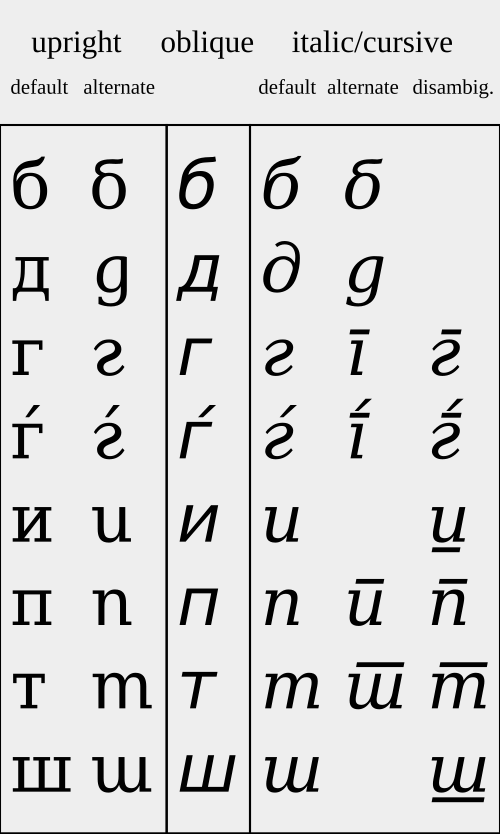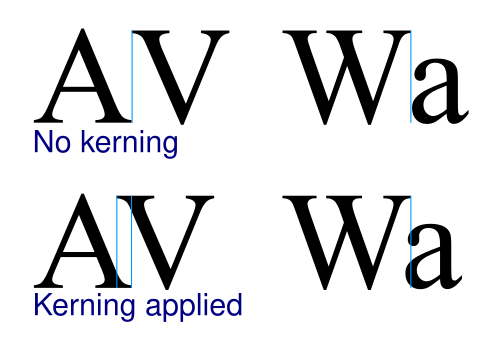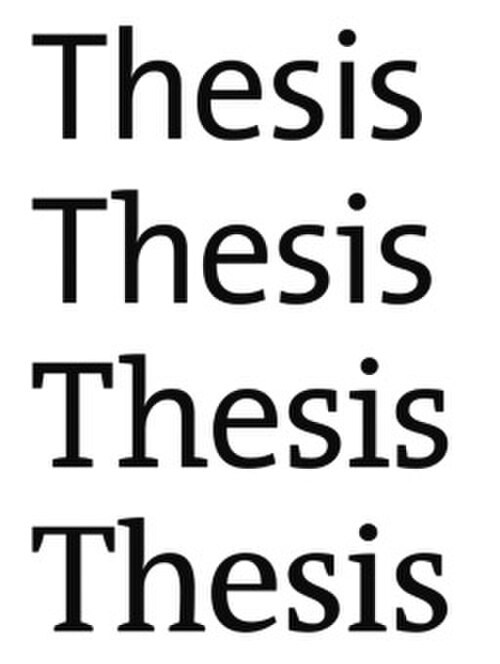
نوع الخط
في الطباعة المعدنية ، يُعرَّف الخط بأنه حجم ووزن ونمط محددين لنوع الخط ، والذي يُعرَّف بأنه مجموعة الخطوط التي تشترك في تصميم عام. على سبيل المثال، يتضمن خط Bauer Bodoni (الموضح في الشكل) الخطوط " Roman 12pt" (أو "عادي") و" bold 12pt " و" italic 12pt " ؛ ويتوفر كل نمط من هذه الأنماط أيضًا في مجموعة من الأحجام الشائعة الأخرى . في الطباعة التقليدية، كانت الخطوط تُصنع فعليًا باستخدام حروف معدنية أو خشبية، مع وجود خط لكل حجم.
في مجال الحوسبة المعاصرة، يُستخدم مصطلحا "الخط" و "نمط الخط" غالبًا بشكل متبادل للإشارة إلى خطوط الحاسوب ، [ 1 ] ومعظمها قابل للتكبير والتصغير. وبينما تستخدم أحجام الخط المختلفة عادةً نفس أشكال الأحرف ، فليس من النادر أن يتضمن الخط عناصر تصميم مختلفة لتحسين سهولة القراءة أو التأثير، خاصةً عند الأحجام الكبيرة أو الصغيرة. تُوزَّع خطوط الحاسوب كملفات، وقد يحتوي كل ملف على وزن واحد أو أكثر ونمط واحد أو أكثر من أنماط الخط.
التهجئة وعلم أصول الكلمات
كلمة font ( في الولايات المتحدة) أو fount (في المملكة المتحدة التقليدية؛ وفي كلتا الحالتين تُنطق / fɒnt / ) مشتقة من الكلمة الفرنسية الوسطى fonte ، والتي تعني " الحديد الزهر". [ 2 ] يشير المصطلح إلى عملية صب الحروف المعدنية في مصنع صب الحروف .
أصبح خط التهجئة ، الذي كان يُستخدم في الأصل في الولايات المتحدة فقط، هو الخط المقبول حاليًا. أما خط Fount ، الذي كان يُستخدم تاريخيًا في المملكة المتحدة ودول الكومنولث ، [ 3 ] فيُعتبر قديمًا.
نوع المعدن
في مطبعة يدوية ( طباعة بارزة )، يشير مصطلح "الخط" إلى مجموعة كاملة من حروف الطباعة المعدنية المستخدمة في طباعة صفحة كاملة. وتُسمى الحروف الكبيرة والصغيرة نسبةً إلى موضع حرف الطباعة المعدني في الطباعة اليدوية: الحرف الكبير الأبعد أو الحرف الصغير الأقرب. ويُستخدم المصطلحان "majuscule" و "minuscule" للدلالة على هذا التمييز .
على عكس الخطوط الرقمية، لا يتضمن الخط المعدني تعريفًا واحدًا لكل حرف، بل يحتوي على أجزاء مادية أكثر للأحرف الشائعة الاستخدام (مثل حروف العلة والنقاط). عند شراء خط جديد، يُباع غالبًا على النحو التالي (على سبيل المثال، في الأبجدية اللاتينية): "12pt 14A 34a"، أي أنه خط بحجم 12 نقطة يحتوي على 14 حرف "A" كبير، و34 حرف "a" صغير.
أما بقية الأحرف، فكانت تُوفَّر بكميات مناسبة لتوزيع الحروف في تلك اللغة. بعض الأحرف المعدنية المطلوبة في الطباعة، مثل الشرطات والمسافات وفواصل ارتفاع الأسطر، لم تكن جزءًا من خط محدد، بل كانت قطعًا عامة يمكن استخدامها مع أي خط. [ 4 ] لا يزال يُطلق على تباعد الأسطر غالبًا اسم " التباعد "، لأن الشرائط المستخدمة لتباعد الأسطر كانت مصنوعة من الرصاص (بدلًا من السبيكة الأكثر صلابة المستخدمة في القطع الأخرى). صُنع شريط التباعد هذا من الرصاص لأنه معدن ألين من قطع الطباعة المعدنية المطروقة التقليدية (التي كانت تتكون جزئيًا من الرصاص والأنتيمون والقصدير )، وبالتالي ينضغط بسهولة أكبر عند تثبيته في "إطار" الطباعة (أي الحامل الذي يجمع جميع الأحرف معًا).
في ثمانينيات وتسعينيات القرن التاسع عشر، تم اختراع الطباعة "بالرصاص الساخن" ، حيث يتم صب الحروف أثناء وضعها، إما قطعة قطعة (كما هو الحال في تقنية Monotype ) أو في أسطر كاملة من الحروف في وقت واحد (كما هو الحال في تقنية Linotype ).
صفات
إضافةً إلى ارتفاع الحرف، عند استخدام المعنى الميكانيكي للمصطلح، توجد عدة خصائص أخرى قد تميز الخطوط، مع العلم أنها تعتمد أيضاً على نظام الكتابة الذي يدعمه الخط. في أنظمة الكتابة الأبجدية الأوروبية ، أي اللاتينية والسيريلية واليونانية ، تتمثل الخصائص الرئيسية في عرض الخط (الوزن) ، والنمط أو الزاوية ، وعرض الحرف .
يُطلق على الخط العادي أو القياسي أحيانًا اسم "روماني " لتمييزه عن الخط العريض أو الرفيع ، وعن الخط المائل أو المائل المائل . غالبًا ما تُحذف الكلمة المفتاحية للحالة العادية الافتراضية في المتغيرات، ولا تُكرر أبدًا، وإلا لكانت تُكتب على النحو التالي: Bulmer regular italic ، Bulmer bold regular ، وحتى Bulmer regular . كما يُمكن أن يُشير مصطلح "روماني" إلى دعم الخط للغات، كاختصار لعبارة "أوروبية غربية".
يمكن استخدام أنماط خطوط مختلفة ضمن نفس نوع الخط في تصميم واحد لتحسين سهولة القراءة والتركيز ، أو في تصميم محدد لجعله أكثر جاذبية بصرية.
وزن
وزن الخط هو سمك الخطوط الخارجية للأحرف بالنسبة إلى ارتفاعها.
قد يتوفر الخط بأوزان متعددة، من الخفيف جدًا إلى العريض جدًا أو الأسود؛ ومن الشائع وجود أربعة إلى ستة أوزان، وبعض الخطوط قد يصل عددها إلى اثني عشر وزنًا. تأتي العديد من الخطوط المستخدمة في المكاتب والويب والاستخدامات غير الاحترافية بوزن عادي وآخر عريض مرتبطين ببعضهما. في حال عدم توفر وزن عريض، تدعم العديد من برامج العرض (المتصفحات، ومعالجات النصوص، وبرامج التصميم الجرافيكي والنشر المكتبي) الخط العريض عن طريق إعادة رسم الخطوط الخارجية مرة ثانية بإزاحة، أو بتمزيقها قليلًا بزاوية مائلة.
يختلف وزن الخط الأساسي بين أنواع الخطوط؛ ما يعني أن أحد الخطوط قد يبدو أكثر سماكة من خط آخر. على سبيل المثال، غالبًا ما تكون الخطوط المستخدمة في الملصقات سميكة افتراضيًا، بينما تكون الخطوط المستخدمة في النصوص الطويلة خفيفة نسبيًا. وقد تختلف تسميات الوزن في أسماء الخطوط فيما يتعلق بوزن الخط الفعلي أو كثافة الأحرف فيه.
أدت محاولات تنظيم نطاق الأوزان إلى تصنيف رقمي استُخدم لأول مرة عام 1957 من قِبل أدريان فروتيجر مع خط Univers : 35 خفيف جدًا ، 45 خفيف ، 55 متوسط أو عادي ، 65 غامق ، 75 غامق جدًا ، 85 غامق جدًا ، 95 غامق جدًا أو أسود . وشملت الأوزان المختلفة "سلسلة 6" (المائلة)، مثل 46 خفيف مائل ، و"سلسلة 7" (الإصدارات المضغوطة)، مثل 57 متوسط مضغوط ، و"سلسلة 8" (المائلة المضغوطة)، مثل 68 غامق مضغوط مائل . ومن خلال هذا النظام الرقمي المختصر، يُصبح من الأسهل تحديد خصائص الخط بدقة، فعلى سبيل المثال، يُترجم "Helvetica 67" (HE67) إلى "Helvetica غامق مضغوط".